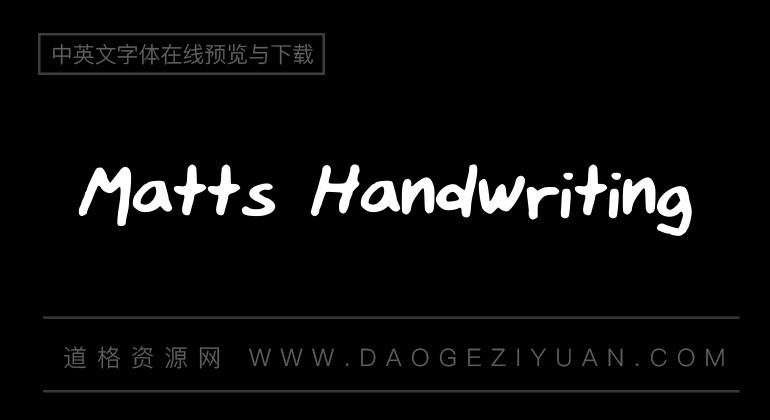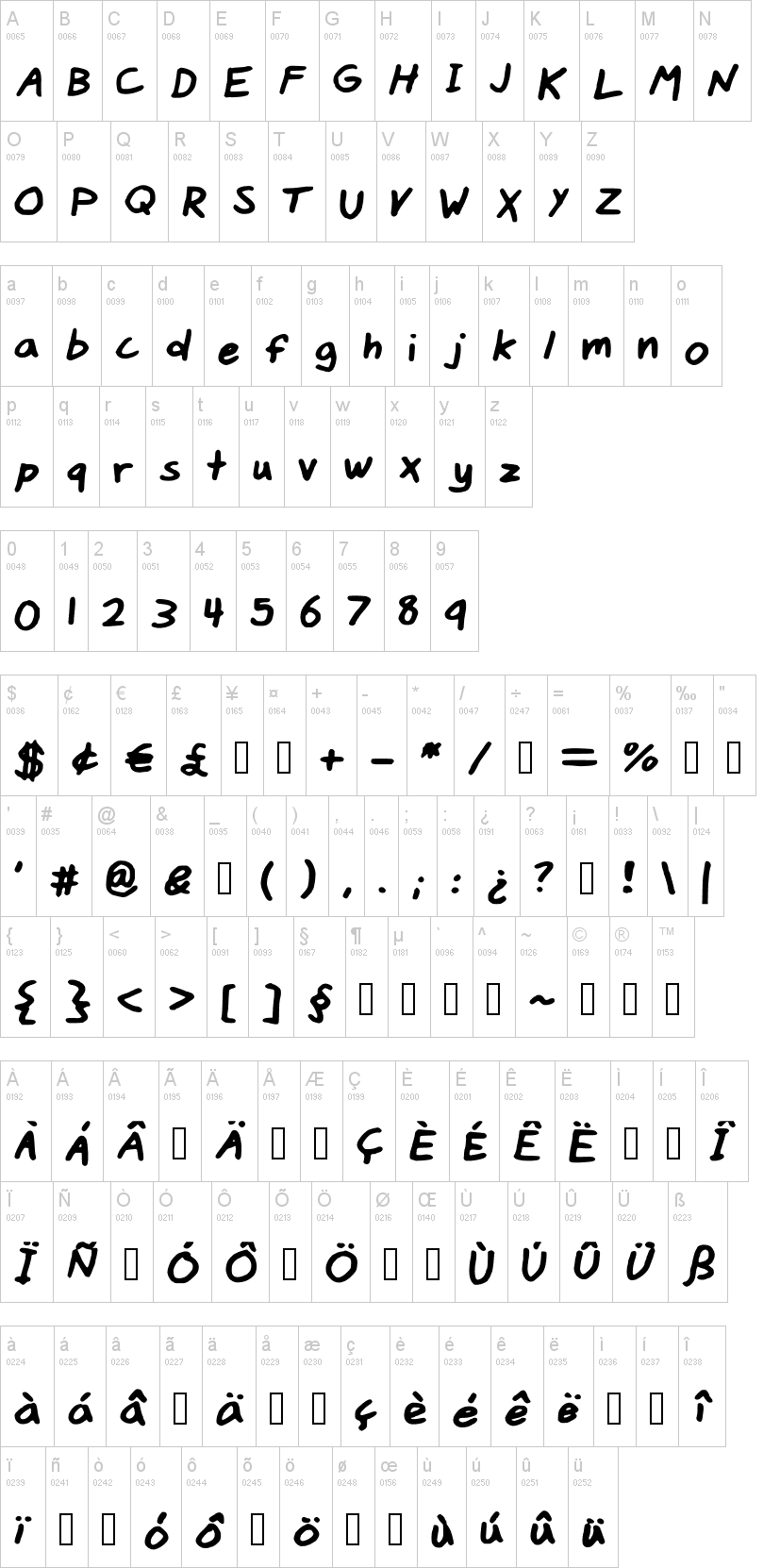
? Matts Handwriting 是一款手写体字体,由英国设计师 Matt McInerney 创作。它具有细腻的笔画,给人一种温暖的感觉,充满了生活气息。它可以用于制作海报、书籍封面、海报、海报、卡片等设计,以及宣传单、标志和标题等。它的特点是清晰的笔画,以及温暖的感觉,让读者有一种亲切的感觉。内容介绍
Matts Handwriting是一款非常不错的手写艺术字体,具有很好的视觉感,适合于文化类的宣传设计、商业类品牌的广告和产品包装设计以及个性化文字排版等较多场景。